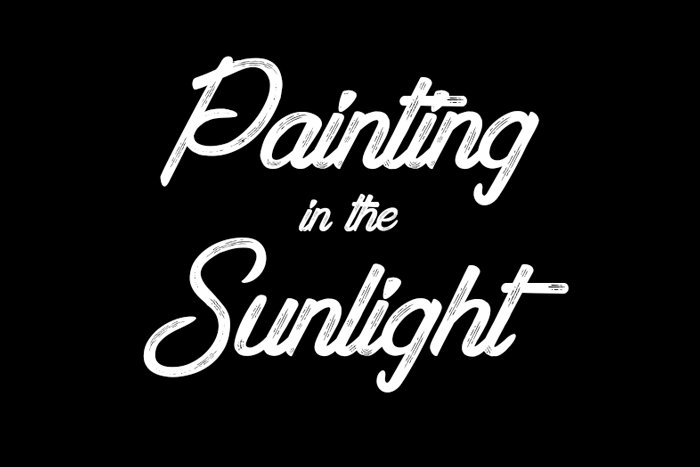
Aqui está uma descrição envolvente para a página de download da font ‘Painting in the Sunlight Font’, com dois parágrafos curtinhos: Nas sombras do dia, onde cada gota de luz se transforma em arte perpétua, encontra-se esta fonte chamada Painting in the Sunlight. Desenhada pela talentosa Cat Butcher, essa fonte é um convite para a criação com uma dose de poesia na forma digital. Seu nome revela um fascínio pelo brilho da natureza solar e sua presença na tela reflete esta ligação íntima com o universo ao seu redor. Aventurando-se nas oportunidades criativas, este fonte atinge o horizonte dos displays digitais oferecendo uma experiência única de letra. Seja para personalizar um logo ou adicionar um toque de vida aos seus projetos gráficos, essa fonte é o quadro perfeito para qualquer artista de design que deseje incorporar a força da natureza na tela. Se você está procurando por uma maneira criativa de expressar seu amor pelo sol e pela arte digital, não hesite em explorar a diversidade e beleza deste fonte. Para obter mais informações ou para adquirir o seu próprio conjunto completo, entre em contato com Cat Butcher através do email mencionado na descrição original da font. Esperamos que ela atinja sua atenção de forma inspiradora.
Designer: Cat Butcher